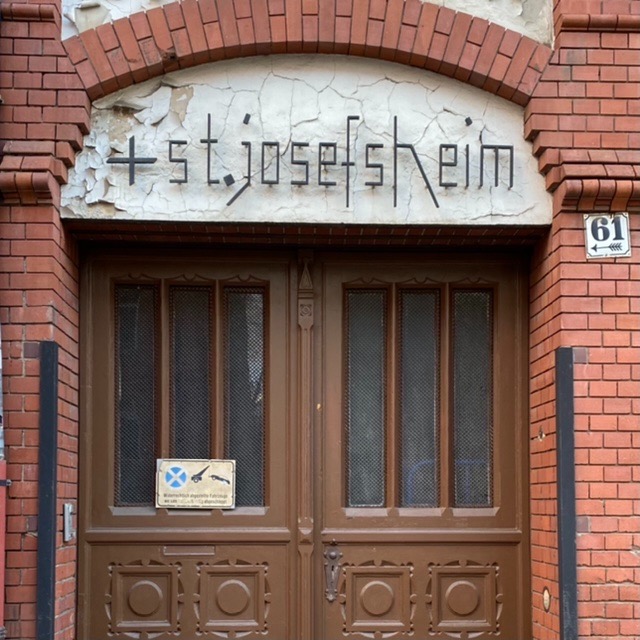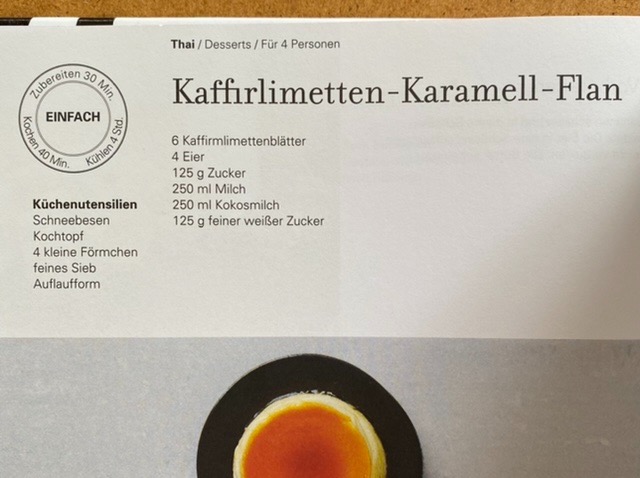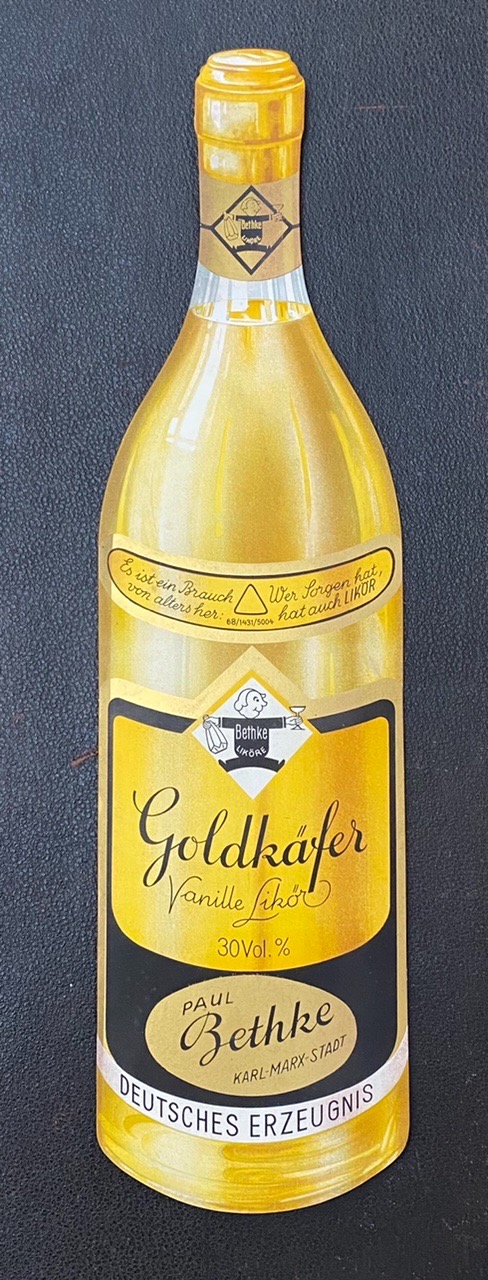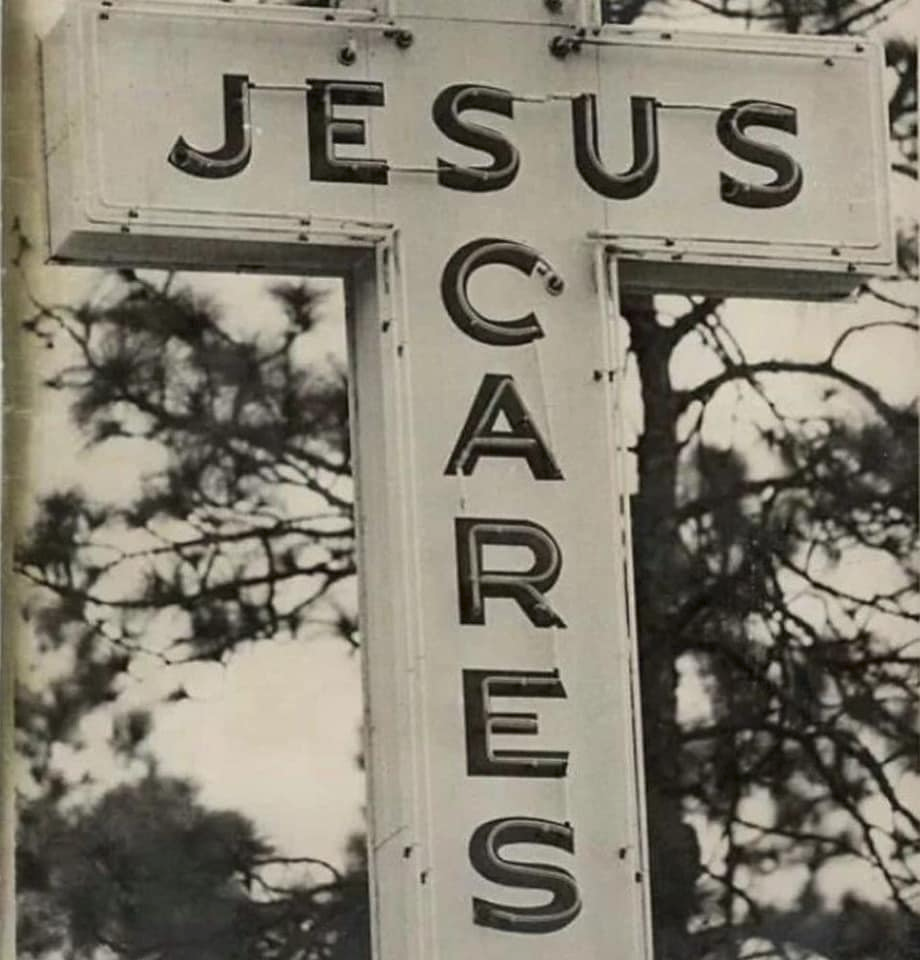
Dieses kleine Fundstück kaufte ich vor knapp drei Monaten in Deutschland für ganze 27 Euro; erst gestern trudelte es ein. Für mich ist sowas die liebste aller Proben, denn sie zeigt komplette Schriften.
Helmut war anscheinend fleißig.
Von der Block habe ich ja schon drei Schritte gemacht. Diese magere wird wohl auch noch dazukommen.
Weiter hinten gibt's Anwendungen.
Und dann noch was besonderes.
Prösterchen! :-P
es ist ein Brauch von alters her...  Doch wer zufrieden und vergnügt, sieht auch zu, daß er welchen kriegt. - sagt Wilhelm Busch im zweiten  Satz.
Auch ein schönes Beispiel dafür, dass ideal-geometrisch konstruierte Körper immer ein bisschen schief aussehen …
Die Poesie von Wilhelm Busch habe ich erst for kurzem (wieder) entdeckt und zu schätzen gelernt. Als Kind habe ich gerne "Das Große Wilhelm Busch Album" meiner Großeltern gewälzt. Vieles ging mir da über den Kopf, jetzt macht es doppelt Spaß. So wie wenn man sich als Erwachsener einen Kinderfilm anschaut, und die ganzen schlüpfrigen Witze mitkriegt, die da so eingebaut sind.
..schätzen gelernt.  Habe ich die schon als Kind. Der in vielen Geschichten imaginäre Zeigefinger hat mich vor mancher  Eselei (Dummheit)  bewahrt.
Und einem Enkel konnte ich neulich klar machen, daß es  mitunter besser ist, sich etwas zu bescheiden:  " Was lange Du begehrt, es wurde Dir beschieden. Du triumphierst und jubelst laut: jetzt hab' ich endlich Frieden. Ach Freundchen, rede nicht so wild , und zähme Deine Zunge!!
Ein jeder  Wunsch, wenn erfüllt, kriegt augenblicklich Junge!
Noch' n  Bush:  Wie wolltest Du Dich unterwinden, die Menschen kurzwegs zu ergründen. Du kennst sie doch nur außenwärts!
Du siehst die Weste, nicht das Herz!
Wahlkampf mit _____________Abstand war auch wichtig :-)
Die Grünen haben deswegen mit _________Abstand die Wahl gewonnen. :nicken:
Alle ›Achtung‹ :nicken:
Die Endbuchstaben finde ich sehr reizvoll und den Gesamtduktus auch – allerdings wirkt mir die Zurichtung nach heutigen Maßstäben etwas ruckelig :-?
Och, das könnte man ja...
mit dem Riss im Putz hab ich zunächst "josefsKeim" gelesen …
… und es hat für die Kaffirlimette nur 1 x für korrekte Rechtschreibung gereicht, bei deren Blättern in der Zutatenliste heißt sie schon Kaffirmlimette. Kommt davon, wenn man nicht einfach die hiesige Bezeichnung Kaffernlimette wählt oder zumindest die übliche Schreibweise Kaffir-Limette.
Oder lieber ein gutes deutsches Kartoffelgericht! :shock:
Bei Kartofel weiß man wenigstens, wie man es schreibt ...
Vielleicht hat es auch nix mit exotischen Namen, sondern einfach mit einem Fehler in der Korrektur zu tun – kommt halt mal vor. :hammer:
[spoiler] Bitte nicht ganz ernst nehmen, es ist freundlich und nicht als Unterstellung gemeint 😉 [/spoiler]
zumindest ist so die Theorie:
:gimmifive:
Die Kaffernlimette und der Kaffernbüffel beziehen sich wohl aber nicht auf das rotwelsche Schimpfwort, sondern lt. wikipedia auf
Kaffer (Plural Kaffern) ist ein vom arabischen Kāfir („Ungläubiger“) abgeleiteter Name, den zuerst die Muslime zwei nichtmuslimischen Völkern beilegten, nämlich den Nuristani (Kafiren) in Zentralasien und den Xhosa im südlichen Afrika.